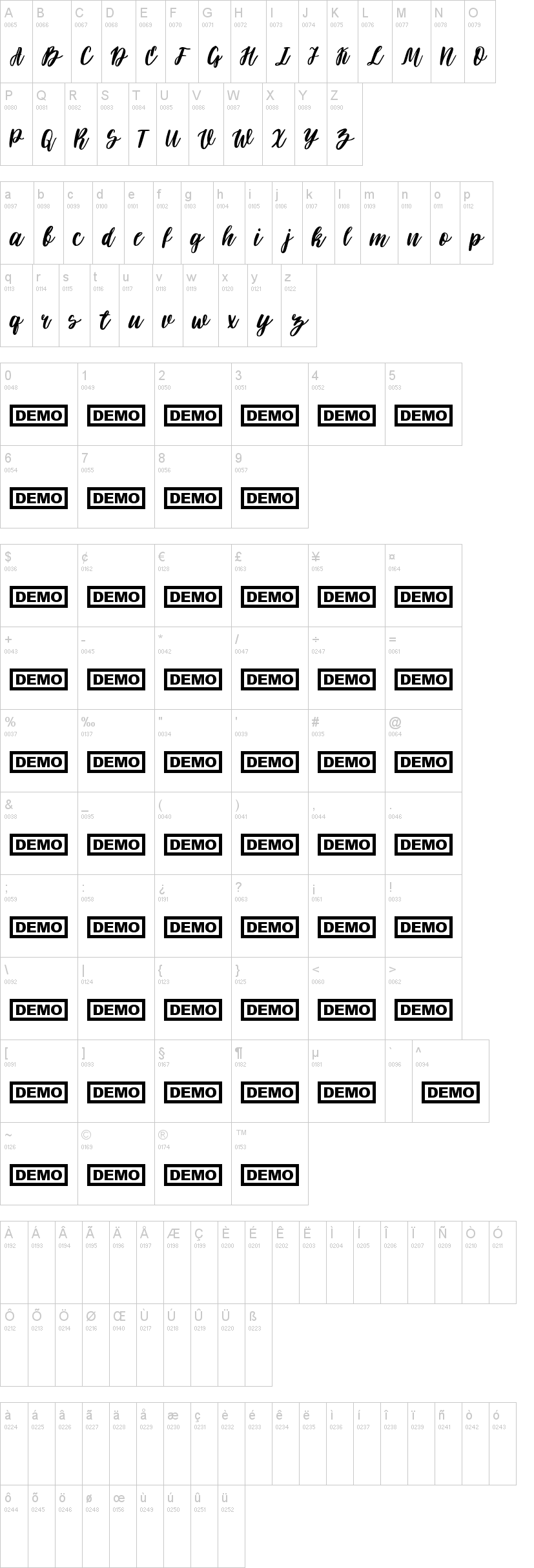
Darflow字体是一款有着复古风格的英文字体。它具有清晰的线条,柔和的曲线,给人一种温暖的感觉。它适用于拥有复古风格的设计,如海报、书籍、海报、标志等,能够提供更多的设计灵感。Darflow字体拥有丰富的字形,可以满足不同的设计需求。它还具有多个字重,可以适应不同的设计风格。内容介绍
Darflow是一款非常不错的手写艺术字体,具有很好的视觉感,适合于文化类的宣传设计、商业类品牌的广告和产品包装设计以及个性化文字排版等较多场景。